Ein Blatt Papier saugt Tinte auf und verzeiht fast jede Unachtsamkeit beim Ansetzen; eine Fensterscheibe schiebt den Kreidemarker einfach beiseite und zeigt jeden zittrigen Schwung gnadenlos. Genau deshalb hält sich hartnäckig der Mythos, für Glas-Lettering an Fenstern und Spiegeln brauche man einen eigenen, hochspezialisierten Kurs. Aus eigener Praxis mit dem Kreidemarker vor dunklen Scheiben kann ich das nicht bestätigen: Ein solider Handlettering-Kurs, der Buchstabenanatomie und Druckaufbau sauber vermittelt, trägt auch auf Glas – wenn man drei Dinge anpasst: das Material, die Körperhaltung und den Umgang mit Fehlern.
Der Mythos vom eigenen Glas-Lettering-Kurs
Der Mythos hält sich hartnäckig, weil Fenster und Spiegel wie ein komplett anderes Handwerk wirken als der Küchentisch. Bevor ich überhaupt einen Marker angesetzt habe, saß ich stundenlang vor Lettering-Videos auf YouTube, ohne ein einziges Mal selbst den Stift in die Hand zu nehmen. Das hat mich keinen Strich weitergebracht, nur die falsche Erwartung geweckt, Glas sei ein komplett neues Handwerk. Die Anatomie der Buchstaben – Oberlänge, Unterlänge, x-Höhe – bleibt trotzdem der Teil, den ich nicht auf Glas neu lerne, sondern von Papier mitbringe. Wer mehrere Kursanbieter nebeneinanderlegt, merkt außerdem schnell: Die Kursstruktur unterscheidet sich oft stärker als der eigentliche Lerninhalt.
Neu ist vor allem die Strichführung selbst. Auf Papier variiere ich mit dem Brush Pen die Linienstärke über den Druck; auf Glas arbeite ich fast immer mit Rundspitzen-Markern, die diesen Druckunterschied kaum zulassen. Ich erinnere mich noch an den Moment auf Papier, als der Aufwärtsstrich mit dem Pinselstift plötzlich so leicht wurde, dass ich kurz die Spitze umgedreht und nach der vermeintlich falschen Seite gesucht habe. Genau dieses Gefühl für Leichtigkeit und Schwere im Strich brauche ich jetzt auf Glas, nur ohne die Hilfe des Drucks. Für die Schattenlinien, die man nachträglich neben den Grundstrich setzt, greife ich auf die Faux-Calligraphy-Technik zurück, ohne sie hier im Detail auszubreiten. Wer sich speziell für saisonale Fensterbilder interessiert, findet in meinem Vergleich zu saisonalen Deko-Kursen ergänzende Ansätze.
Was ändert sich wirklich, wenn Buchstaben auf Glas wandern?
Die Druckkurve, die man beim Brush Pen auf Papier trainiert, lässt sich nicht eins zu eins auf den Kreidemarker übertragen, weil die Spitze selbst kaum nachgibt – der Effekt kommt jetzt aus der Linienbreite des Markers, nicht aus der Handbewegung. Welches Papier zu welchem Stift passt, ist ohnehin ein eigenes Kapitel für sich; auf Glas stellt sich die Frage anders, denn hier zählt vor allem, wie glatt die Spitze über die Fläche gleitet. Ein Brush Pen nutzt sich bei jeder Übungseinheit sichtbar an der Spitze ab, während der Kreidemarker eher an der Ventilspitze leidet – zwei unterschiedliche Verschleiß-Geschichten, die ich mittlerweile getrennt im Kopf behalte. Wer nur die Papier-Übung kennt, unterschätzt oft, wie viel Kontrolle allein aus dem Arm statt aus den Fingern kommen muss, sobald die Fläche senkrecht steht.
Abwischbare Kreidemarker verzeihen mehr als permanente Lackstifte
Flüssigkreidemarker sind für nicht-poröse Flächen wie Glas gemacht, und die gängigen Spitzenbreiten reichen von etwa 1 mm bis 15 mm mit sehr unterschiedlichen Einsatzgebieten. Für kleine Sprüche auf dem Flurspiegel eignet sich eine Spitze um 1 bis 2 mm, während großflächige Küchenfenster erst ab etwa 8 mm wirklich Wirkung zeigen. Auf die Idee, mich intensiver mit Kreidemarkern zu beschäftigen, hat mich ausgerechnet ein Marktstand auf dem Wochenmarkt Bad Godesberg gebracht, der seine Tagesangebote in sauberen Versalien auf eine kleine Tafel schrieb. Genau die Optik wollte ich danach auf dem eigenen Fenster nachbauen. Eine Leserin, Andrea Helbig, hat mich kürzlich über das Kontaktformular nach der passenden Spitzenbreite für einen Flurspiegel gefragt, und typisch für sie hatte sie da schon drei verschiedene Markerstärken selbst getestet, bevor sie überhaupt schrieb. Abwischbare Kreidemarker ermöglichen dabei eine deutlich entspanntere Lernkurve als permanente Lackmarker, weil die Hemmschwelle sinkt: Sitzt ein Schwung nicht, wischt man ihn weg und setzt neu an, was das Muskelgedächtnis schneller schult als das vorsichtige Arbeiten mit dauerhaften Stiften.
Ein Kniff, den ich erst nach ein paar missglückten Versuchen verinnerlicht habe, ist das sogenannte Ghosting: Man klebt die Vorlage von außen gegen die Scheibe und zeichnet sie von innen nach. Das klingt einfach, verlangt aber eine ruhige Hand, weil die Lichtbrechung im Glas eine kleine optische Verschiebung erzeugt. Genau diese systematische Herangehensweise finde ich im Handlettering-Kurs von Timothy90 wieder, der seit mehreren Jahren stabil auf Digistore24 aktiv ist – für mich ein Argument gegen Eintagsfliegen-Anbieter, wenn ich mein Übungsmaterial auswähle.
Digitale Vorbereitung erspart den Putzlappen
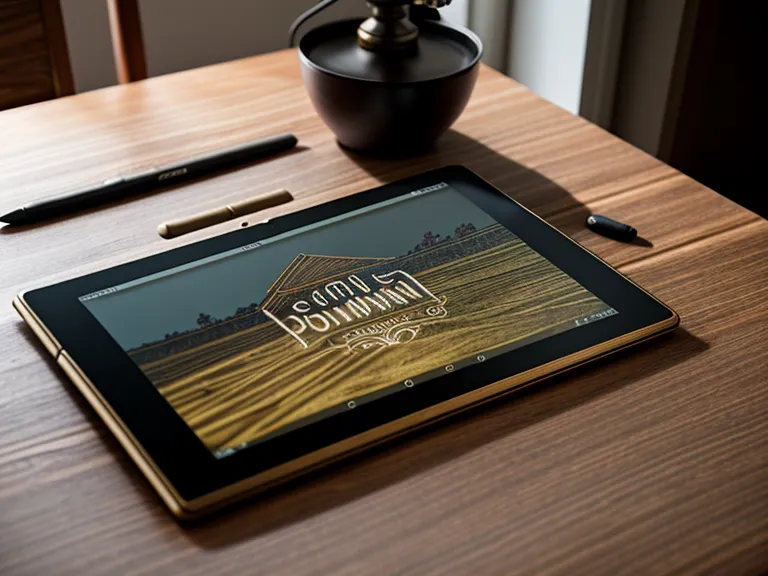
Statt direkt auf dem Glas zu improvisieren und mich über schiefe Proportionen zu ärgern, skizziere ich Layouts inzwischen zuerst auf dem iPad Pro mit 12,9-Zoll-Display in Procreate. Ich fotografiere das Fenster, lege das Foto als unterste Ebene an und baue den Schriftzug direkt darüber auf, was am Ende viel Zeit mit dem Mikrofasertuch spart. Meine Bürokollegin Ursula Kettner würde hier vermutlich sofort zum iPad greifen, denn sie bevorzugt ohnehin digitale Notizen gegenüber Papier-Übungsblättern; für die Vorbereitung auf Glas ist das ein klarer Vorteil, weil man das Layout am Bildschirm klärt, bevor der erste Strich auf die Scheibe kommt. Was am Wochenende bei uns am Küchentisch dann oft wie ein kleiner kreativer Workshop endet, ist letztlich nur ein weiterer Analog-Digital-Transfer – nur mit Fensterglas statt Skizzenbuch als Ziel. Wer diesen Weg von Grund auf lernen will, findet dazu mehr im Vergleich zu Digital Lettering ohne Vorkenntnisse.
Sobald der Entwurf auf dem iPad steht, drucke ich ihn aus oder nutze ihn als visuelle Referenz beim Übertragen. Für kleine Symbole wie Blumenranken oder Osterhasen hilft eine eigene kleine Symbolbibliothek, wie man sie sich in einem Sketchnotes-Kurs aufbaut – nur eben für Fensterdeko statt für Notizen. Komplexe Formen in einfache Symbole zu zerlegen, ist gerade auf Glas hilfreich, weil man dort oft in mehreren Etappen arbeitet statt in einem Zug durchzuschreiben. Wer sich für digitale Zeichentechniken auf dem iPad allgemein interessiert, findet weitere Details im Vergleich der Sketchnotes-Kurse für das iPad.
Aus der Schulter schreiben, nicht aus dem Handgelenk
Das eigentliche Geheimnis bei großflächigen Fenstern liegt nicht im Handgelenk, sondern in der Bewegung aus der Schulter heraus. Wer nur aus den Fingern schreibt, verkrampft auf senkrechtem Glas innerhalb von zehn Minuten, weil die Fläche keine Auflage bietet wie der Küchentisch. Das ist am Ende auch eine Frage der Schreibhaltung: Wer dauerhaft nur aus dem Handgelenk arbeitet, spürt die Ergonomie-Folgen spätestens am Fenster, wo man weder sitzen noch die Hand auflegen kann. Wie viel Übungsvolumen für sichtbaren Fortschritt nötig ist, hängt dabei stärker von der Regelmäßigkeit ab als von der reinen Stundenzahl – ein eigenes Thema, das über den Rahmen dieses Vergleichs hinausgeht. Die Übungen zur Strichführung aus einem soliden Handlettering-Kurs lassen sich eins zu eins auf die Glasfläche übertragen, sofern man den Oberkörper mitbewegt.